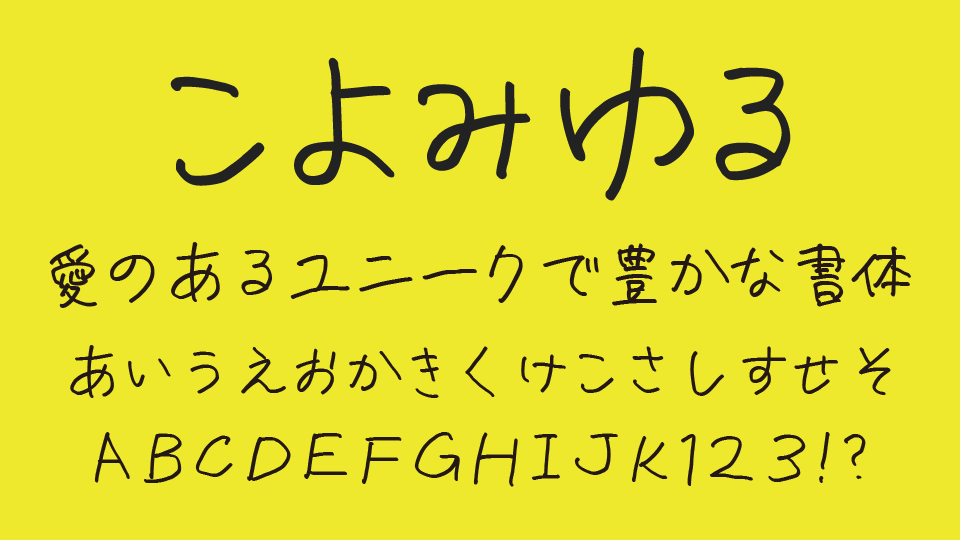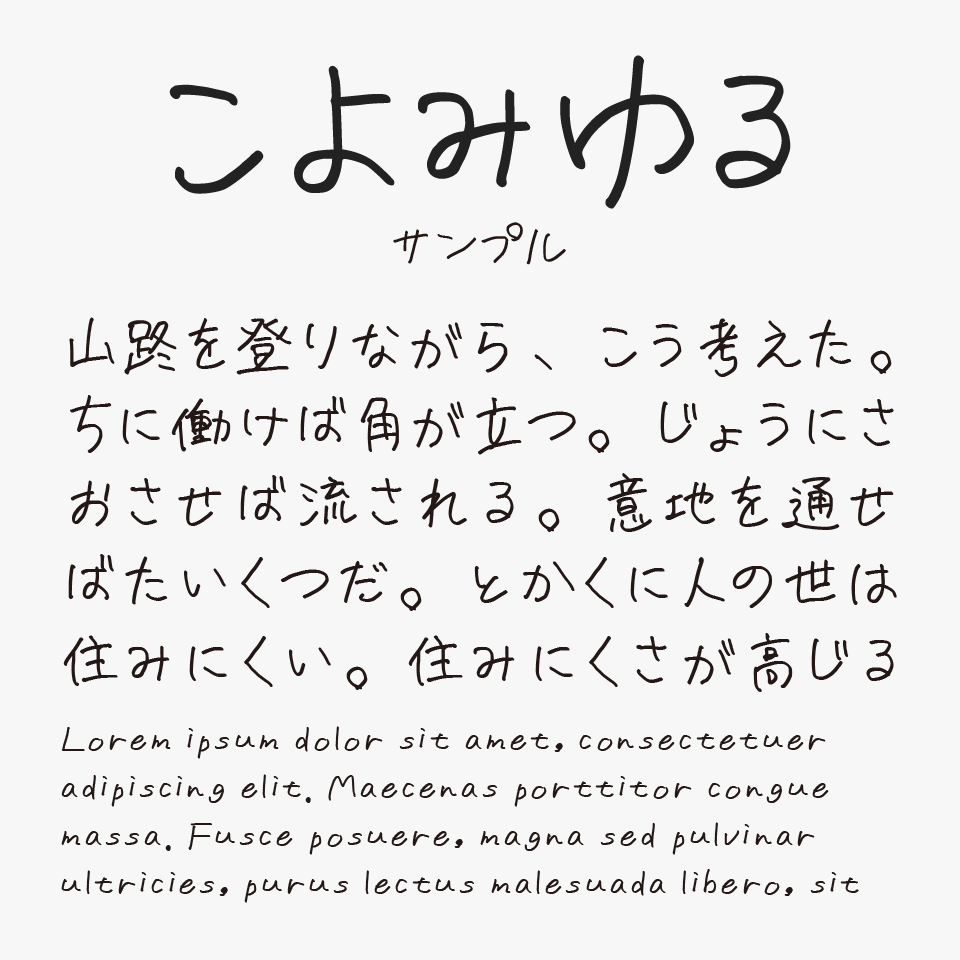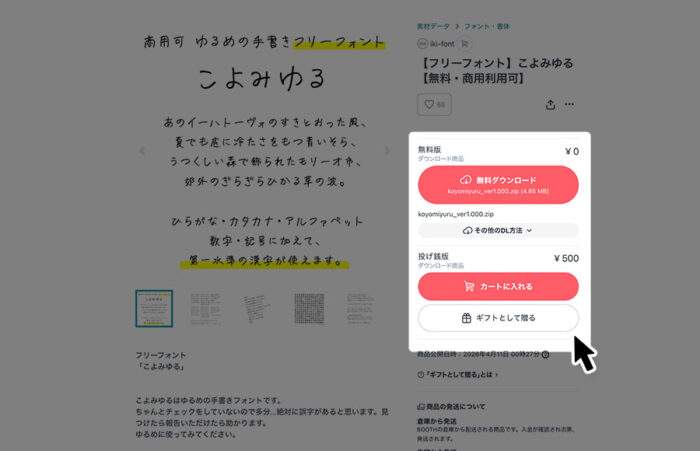
こよみゆる
こよみゆるフォントは、ペンで気ままに書き記したような、ゆるめな揺らぎと温もりを持つ手書きフォントです。
線の強弱はほとんどなく一定の細さで統一されていますが、文字ごとに微妙な傾きや形の揺れがあり、丁寧に書かれた日常のメモのようなゆるさを感じさせられるとってもステキな手書き文字です。
収録文字は、漢字(第一水準漢字(2965字))・ひらがな・カタカナ・アルファベット・数字・記号が収録されています。